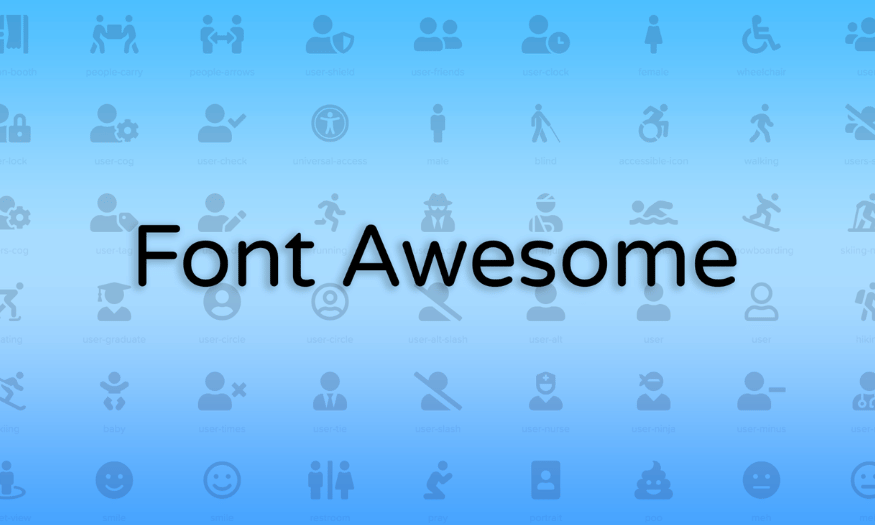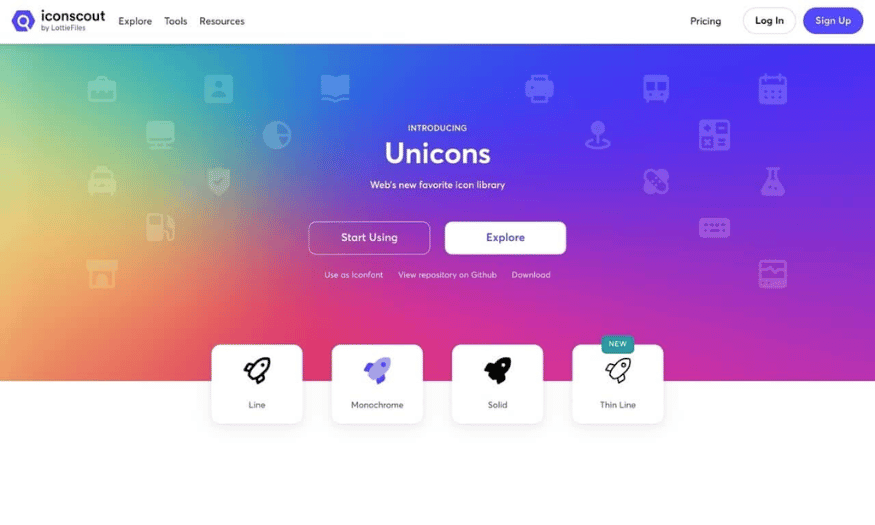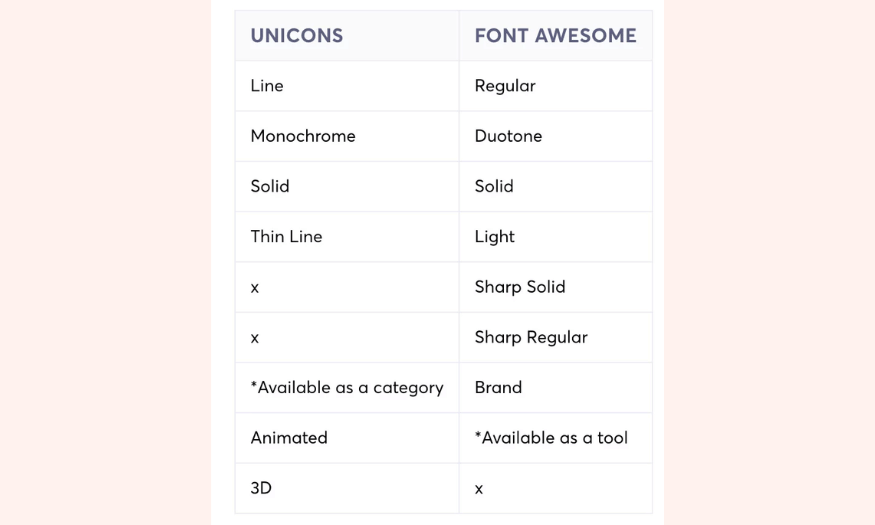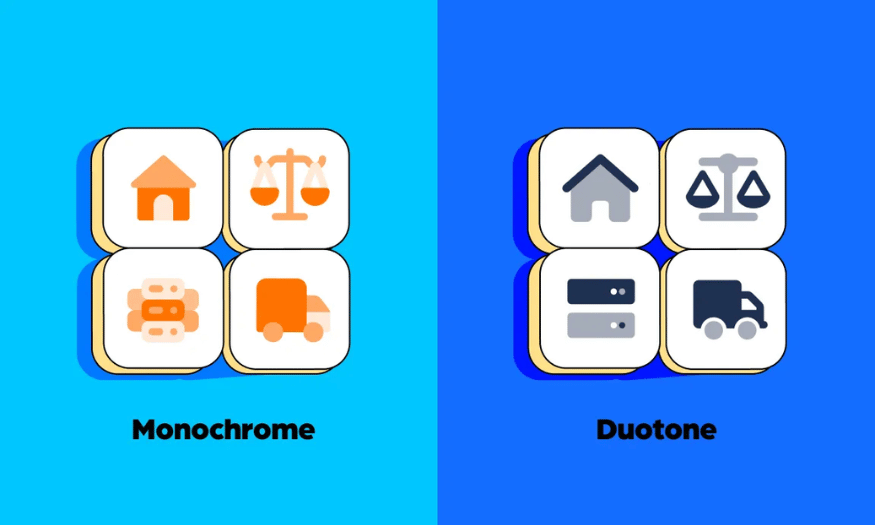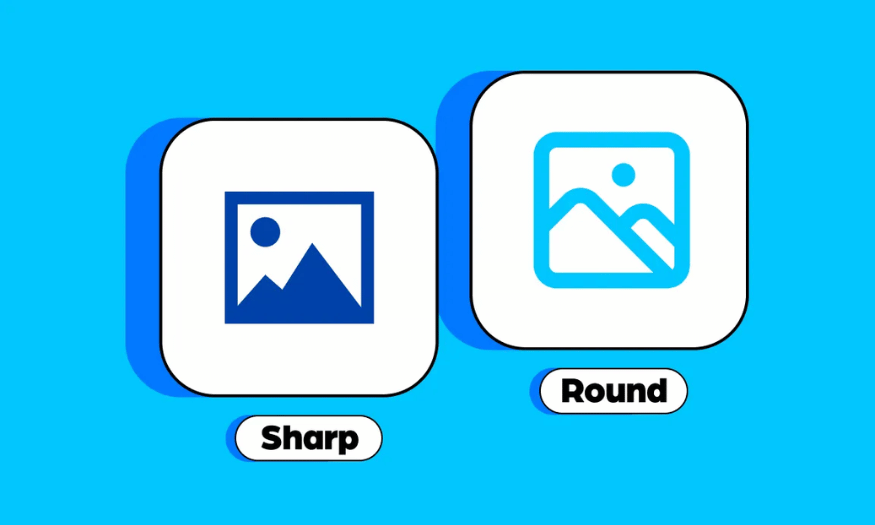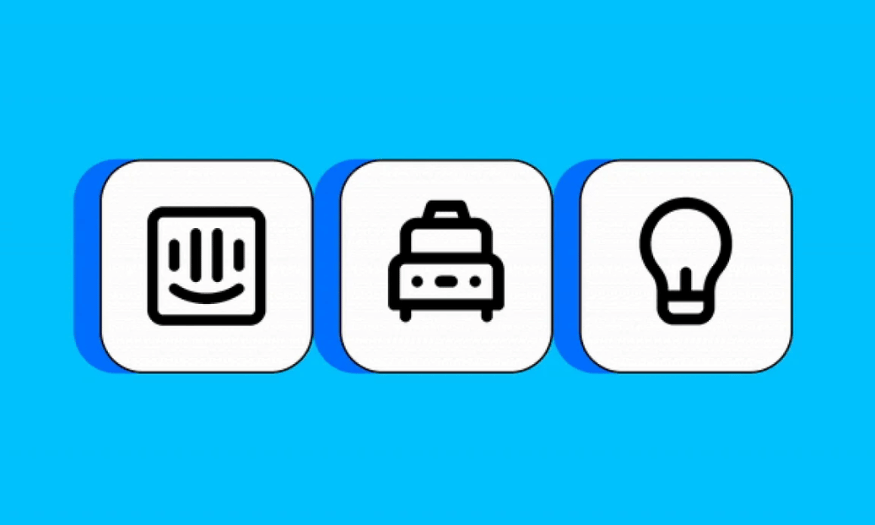
Sự Khác Biệt Giữa Unicons Và Font Awesome
Trong thế giới thiết kế web, biểu tượng (icon) đóng vai trò quan trọng trong việc cải thiện trải nghiệm người dùng cũng như truyền tải thông điệp một cách trực quan. Hai bộ biểu tượng phổ biến hiện nay là Unicons và Font Awesome. Mặc dù cả hai đều cung cấp một loạt các biểu tượng đa dạng, nhưng chúng lại có những sự khác biệt đáng kể về cách sử dụng, tính năng và phong cách thiết kế. Bài viết này Sadesign sẽ phân tích và so sánh hai bộ biểu tượng này để giúp bạn lựa chọn bộ biểu tượng phù hợp nhất cho dự án của mình.
Sự Khác Biệt Giữa Unicons Và Font Awesome
Trong thế giới thiết kế web, biểu tượng (icon) đóng vai trò quan trọng trong việc cải thiện trải nghiệm người dùng cũng như truyền tải thông điệp một cách trực quan. Hai bộ biểu tượng phổ biến hiện nay là Unicons và Font Awesome. Mặc dù cả hai đều cung cấp một loạt các biểu tượng đa dạng, nhưng chúng lại có những sự khác biệt đáng kể về cách sử dụng, tính năng và phong cách thiết kế. Bài viết này Sadesign sẽ phân tích và so sánh hai bộ biểu tượng này để giúp bạn lựa chọn bộ biểu tượng phù hợp nhất cho dự án của mình.
1. Giới thiệu về Font Awesome
Font Awesome là một trong những bộ biểu tượng tiên phong và được ưa chuộng nhất trong thế giới thiết kế web. Ra mắt vào năm 2012, Font Awesome đã nhanh chóng thu hút sự chú ý với phiên bản đầu tiên của thư viện biểu tượng mã nguồn mở. Với hàng nghìn biểu tượng phong phú, Font Awesome phục vụ cho nhiều nhu cầu khác nhau, từ giao diện người dùng đến các yếu tố xã hội. Thư viện này không chỉ cung cấp biểu tượng, mà còn cho phép tùy chỉnh và định dạng thông qua Cascading Style Sheets (CSS), mang lại sự linh hoạt tối đa cho các nhà phát triển.
Điểm nổi bật của Font Awesome là sự liên tục cập nhật và cải tiến. Hiện tại, thư viện đã phát triển đến phiên bản thứ sáu, với hàng loạt biểu tượng mới được thêm vào để đáp ứng các xu hướng thiết kế hiện đại. Bằng cách này, Font Awesome không chỉ giữ vững vị trí của mình trong lòng người dùng mà còn khẳng định vai trò quan trọng trong việc định hình xu hướng thiết kế web. Với giao diện dễ sử dụng và tài liệu hướng dẫn chi tiết, Font Awesome trở thành lựa chọn hàng đầu cho các nhà thiết kế muốn tích hợp biểu tượng chất lượng cao một cách dễ dàng.
2. Giới thiệu về Unicons
Trong khi Font Awesome đã có chỗ đứng vững chắc trên thị trường, Unicons lại là một cái tên mới nổi, nhưng không kém phần ấn tượng. Được phát triển bởi IconScout, Unicons cung cấp hơn 4.500 biểu tượng và phông chữ biểu tượng SVG, với hơn 21 danh mục khác nhau. Một trong những lợi thế lớn của Unicons là khả năng cung cấp các thiết kế hiện đại, phù hợp với xu hướng mới nhất trong ngành thiết kế. Điều này giúp Unicons thu hút được sự quan tâm của những nhà thiết kế trẻ tuổi và những người yêu thích sự đổi mới.
Không chỉ dừng lại ở việc cung cấp biểu tượng, Unicons còn nằm trong hệ sinh thái lớn hơn của IconScout, nơi người dùng có thể truy cập vào hơn 5,7 triệu tài sản thiết kế khác nhau. Điều này mang lại cho Unicons một lợi thế cạnh tranh mạnh mẽ, vì người dùng không chỉ tìm thấy biểu tượng mà còn có cơ hội khám phá hình minh họa, hình ảnh 3D, và cả hoạt hình Lottie. Sự kết hợp này tạo ra một bộ công cụ toàn diện cho các nhà thiết kế, giúp họ dễ dàng hơn trong việc phát triển và thực hiện các ý tưởng sáng tạo.
3. Phân tích các phong cách biểu tượng
3.1 Biểu tượng đa dạng
Trong bối cảnh thiết kế hiện đại, phong cách biểu tượng là yếu tố không thể thiếu. Unicons và Font Awesome đều nổi bật với nhiều phong cách biểu tượng khác nhau, giúp người dùng dễ dàng lựa chọn phù hợp với ngữ cảnh thiết kế của họ. Unicons tự hào với 6 phong cách riêng biệt, trong khi Font Awesome cung cấp đến 7 phong cách, tạo nên một cuộc cạnh tranh thú vị giữa hai thư viện này. Sự đa dạng này không chỉ giúp tăng tính linh hoạt trong thiết kế mà còn mở ra nhiều khả năng sáng tạo cho các nhà phát triển và nhà thiết kế.
Điều đặc biệt ở đây là sự khác biệt trong cách mà mỗi thư viện tiếp cận phong cách biểu tượng. Mỗi phong cách đều có những đặc trưng riêng, từ đường nét, độ dày cho đến cách sử dụng màu sắc. Việc hiểu rõ từng phong cách sẽ giúp các nhà thiết kế lựa chọn được biểu tượng phù hợp nhất cho dự án của mình, từ những thiết kế tối giản cho đến những thiết kế cầu kỳ và phong phú.
3.2 Biểu tượng line và solid
Một trong những phong cách biểu tượng cơ bản và phổ biến nhất là biểu tượng line và solid. Unicons gọi phong cách này là biểu tượng line, trong khi Font Awesome lại gọi là regular. Biểu tượng line được thiết kế với các đường nét mảnh mai, mang đến một vẻ ngoài thanh thoát và dễ đọc. Ngược lại, biểu tượng solid có phần bên trong được tô đậm, tạo nên một hình ảnh mạnh mẽ và nổi bật. Sự khác biệt này không chỉ tạo ra hiệu ứng thị giác khác nhau mà còn mang lại cảm xúc và thông điệp khác nhau cho người xem.
Cả hai phong cách này đều có thể dễ dàng tích hợp vào các thiết kế khác nhau, từ các trang web thương mại điện tử đến ứng dụng di động. Việc lựa chọn giữa chúng phụ thuộc vào ngữ cảnh sử dụng và cảm xúc mà nhà thiết kế muốn truyền tải. Sự kết hợp khéo léo giữa biểu tượng line và solid có thể tạo ra những thiết kế độc đáo và ấn tượng, làm nổi bật thương hiệu và sản phẩm một cách hiệu quả.